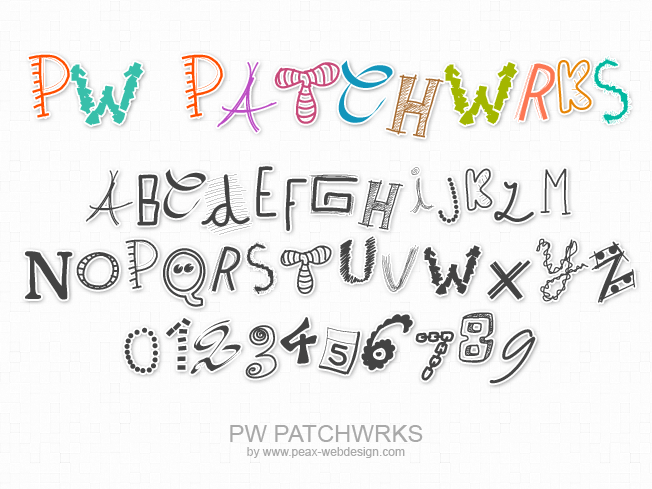
PW Patchwrks est une nouvelle police d'écriture un peu enfantine et ludique, dont chacune des lettres est différente. Vous pourrez l'utiliser gratuitement pour tous vos projets personnels. Pour un projet commercial, merci de me contacter.